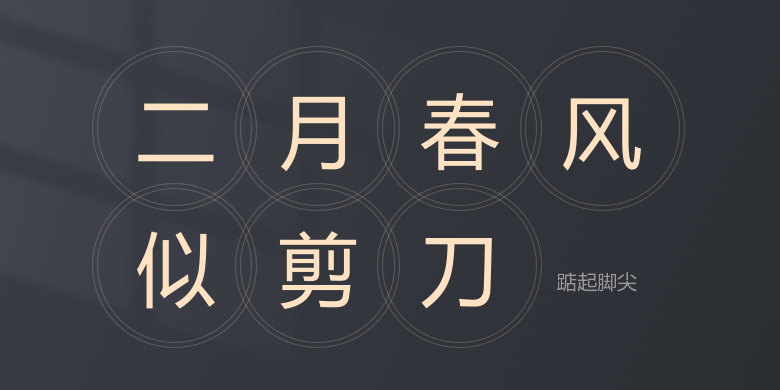
踮起脚尖
踮起脚尖,这款字体结构工整、笔画清晰,兼顾美观与易读性,适用于标题、正文、海报、包装、LOGO 等多种场景。字形优雅稳定,风格百搭耐看,适配日常排版与创意设计,让文字呈现更舒适、更具质感。踮起脚尖一笔一画,皆是细节,以均衡的比例、流畅的线条打造舒适视觉体验,字形端正大气,风格简约现代。无论是商业设计、品牌宣传还是日常排版,都能轻松驾驭,让文字更有格调与力量。踮起脚尖字体下载。